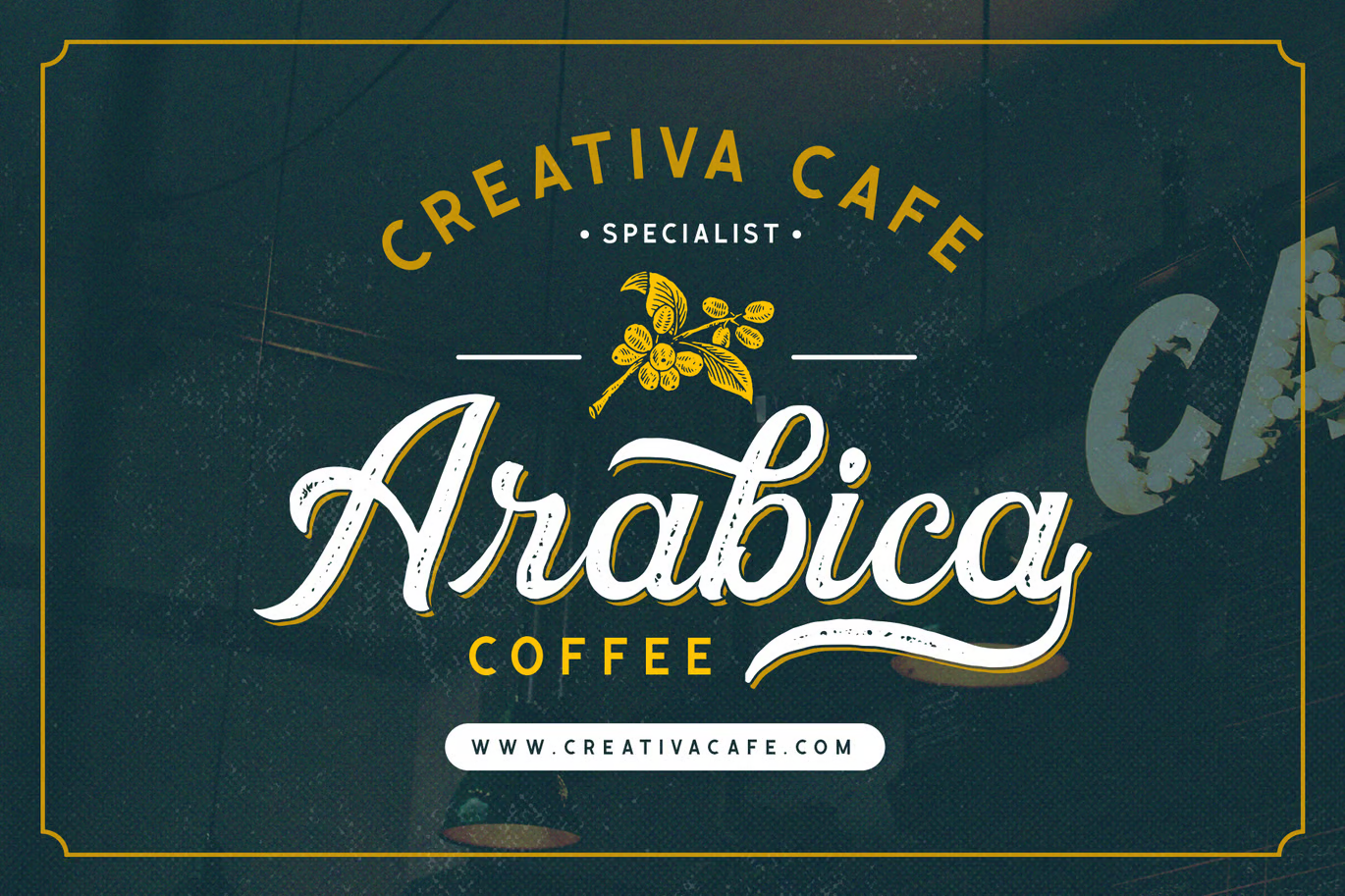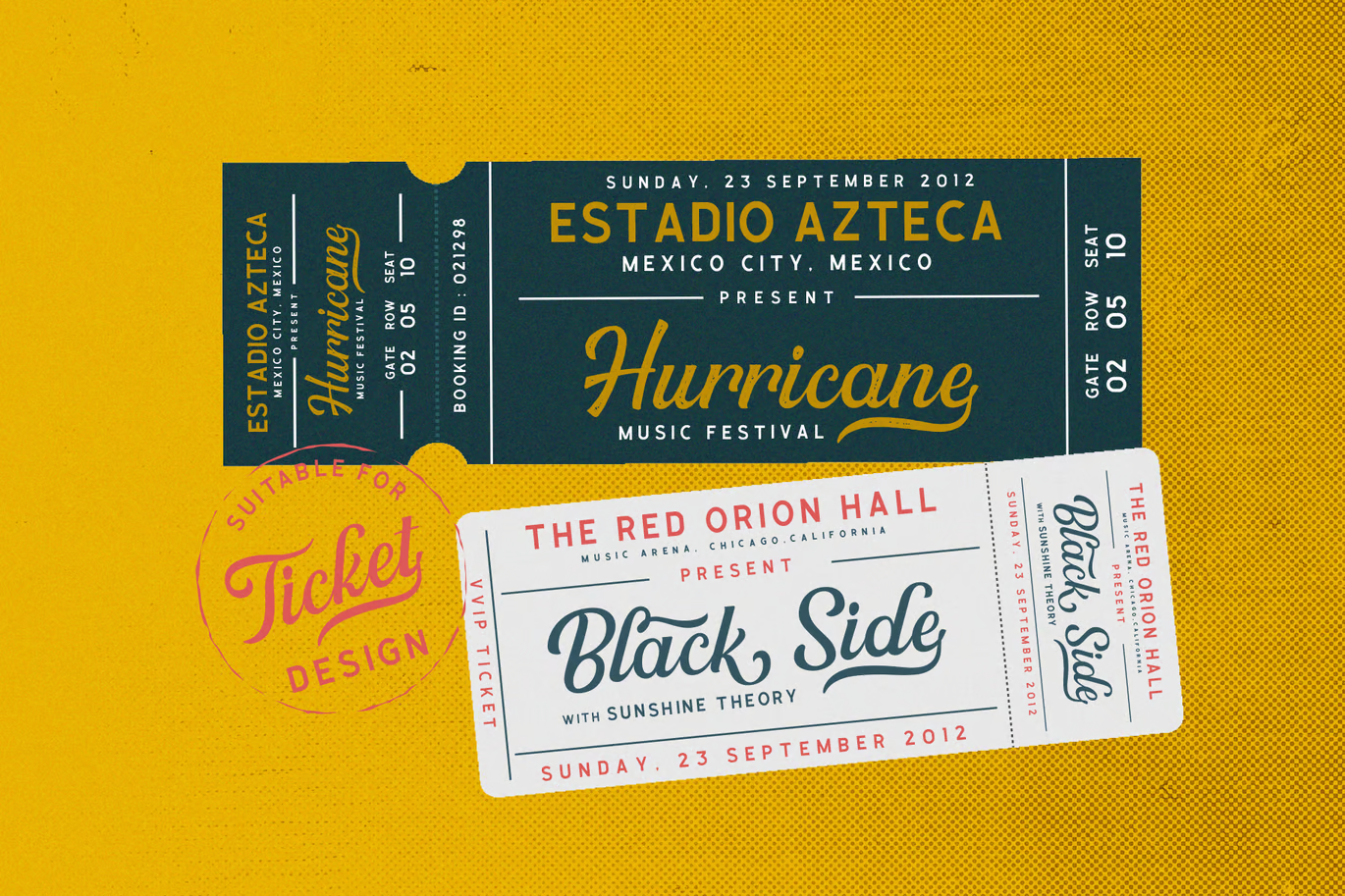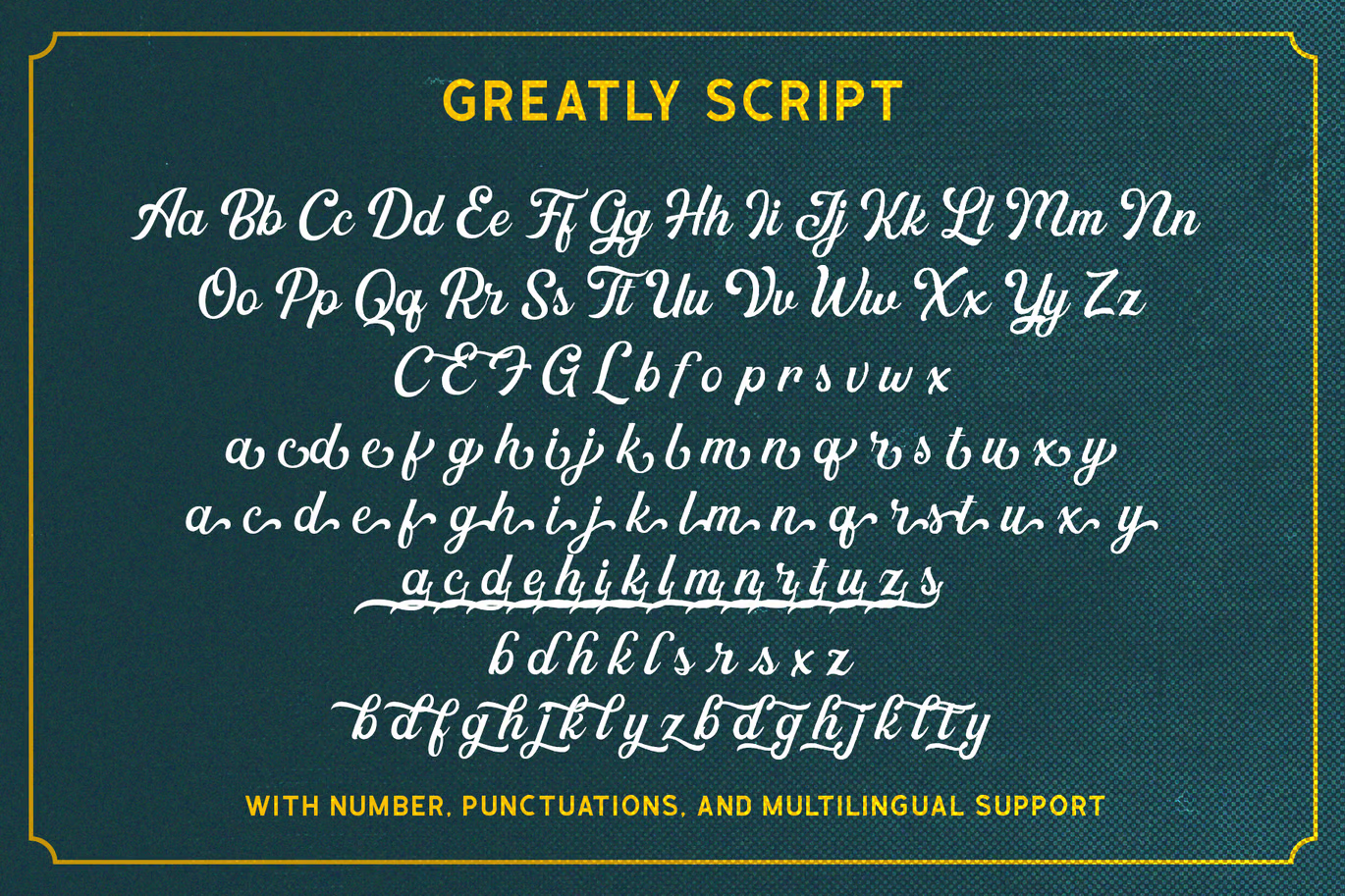
Greatly Font
Description de Greatly Font
Greatly Font Duo est un duo de polices script et sans empattement de letterhend, qui conviennent à la création de designs élégants et frais. Ces deux polices sont très utiles dans tout projet de design, notamment lorsque vous souhaitez concevoir des logos, des vêtements, des invitations et des marques.